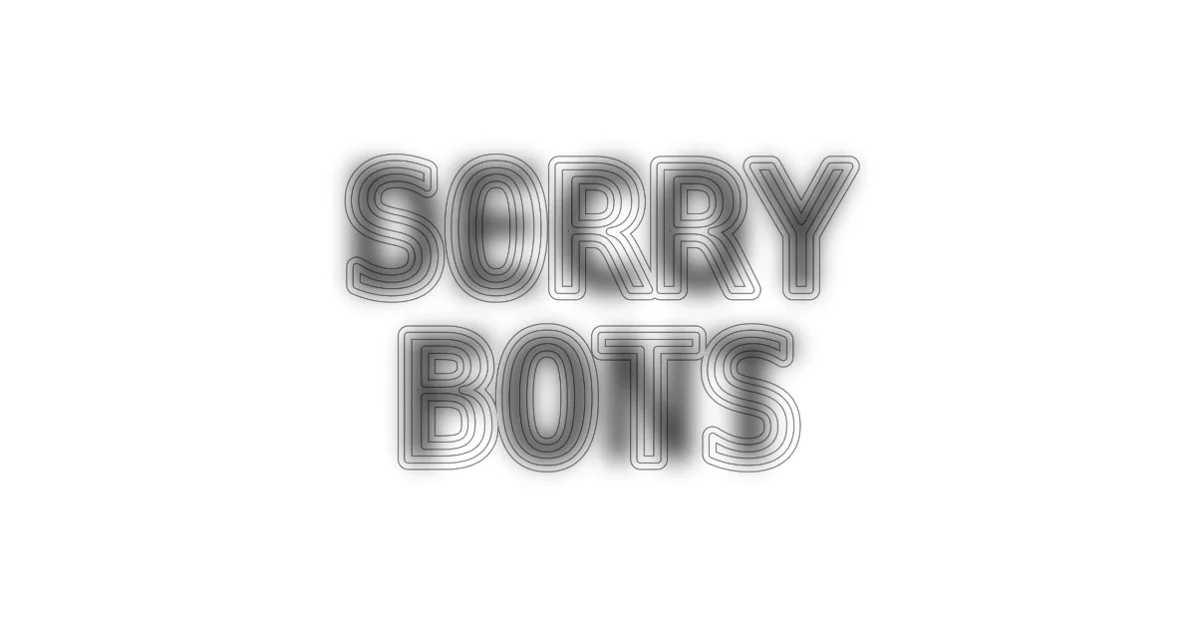
AI 텍스트 인식 회피를 위한 'Decoy Font' TTF 폰트가 공개됨
공간 주파수(Spatial Frequency) 기술을 활용하여 인간과 AI가 다르게 인식하도록 설계됨
ChatGPT, Gemini 등 최신 LLM도 이미지 텍스트 인식에 실패하는 사례 제시
이 폰트는 하이브리드 이미지(Hybrid Image) 기법을 타이포그래피에 적용한 것으로, 앨버트 아인슈타인-마릴린 먼로 혼합 이미지와 같은 원리를 활용합니다. 전경의 얇은 윤곽선과 배경의 저주파수 덩어리를 결합하여, 보는 거리에 따라 다른 메시지를 전달하는 방식입니다. 이는 공간 주파수(Spatial Frequency)의 차이를 이용해 인간의 시각과 AI의 픽셀 기반 분석 간의 인식 차이를 공략하는 기술입니다.
커뮤니티에서는 ChatGPT, Claude, Gemini 등 다양한 최신 LLM이 Decoy Font를 제대로 인식하지 못하는 사례가 공유되었습니다. 특히 초기에는 숨겨진 메시지를 파악하지 못하지만, '숨겨진 텍스트가 있다'는 힌트가 주어지면 일부 모델은 이를 파악하는 모습을 보였습니다. 이는 AI의 텍스트 인식 방식이 인간의 다각적이고 맥락적인 이해와는 다르다는 점을 시사하며, AI 환각(Hallucination) 현상과도 연관 지어 볼 수 있습니다.
일부 사용자들은 이 폰트의 실용성에 의문을 제기하며, AI의 발전 속도를 고려할 때 이러한 기법이 장기적으로 AI의 텍스트 인식 능력을 효과적으로 막을 수 있을지에 대해 회의적인 반응을 보입니다. 또한, 스크린 리더 사용자에게는 경험을 저해할 수 있다는 지적도 있습니다. PIL 스크립트나 간단한 필터링으로도 쉽게 무력화될 수 있다는 의견은, 이 기술이 완벽한 보안 솔루션이 아닌 일종의 예술적 시도에 가깝다는 평가로 이어집니다.
이 폰트는 AI의 정보 수집 능력에 대한 인간의 창의적인 저항을 보여주는 사례로 주목받고 있습니다. 비록 완벽한 보안책은 아닐지라도, AI 시대에 인간과 기계의 상호작용에 대한 흥미로운 질문을 던집니다. 일부에서는 이를 '예술'로 규정하며, AI를 '싸우는' 방식보다는 인간과 AI의 공존을 모색하는 관점에서 접근해야 한다는 의견도 제시되었습니다.